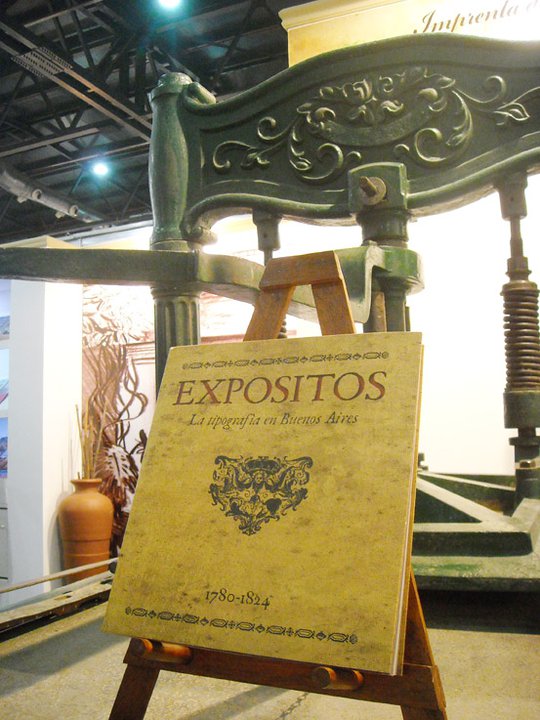
Expósitos + Gazeta
Expósitos.
La tipografía en Buenos Aires
1780-1824 |
El diseñador en Comunicación Visual Fabio Ares, egresado de la Universidad Nacional de La Plata en su libro, propone un recorrido histórico por la que fuera la primera imprenta porteña: la Imprenta de Niños Expósitos, además, los antecedentes de la impresión en Europa y en los “dominios” españoles en América; cómo era la ciudad que la recibió en 1780; los motivos e ideas que dieron contenido a sus impresos; y los aspectos técnicos de la impresión tipográfica de aquellos tiempos.
Por otra parte, presenta una reconstrucción tipográfica de los primeros caracteres y ornamentos utilizados, realizada a partir de documentos impresos que integran el fondo documental del Gobierno de la Ciudad.
La Gazeta
de Buenos Ayres |
El 7 de junio de 1810 se publica el primer número de "Gazeta de Buenos Ayres", con Mariano Moreno como editor, para difundir esta etapa independentista que comenzaba.